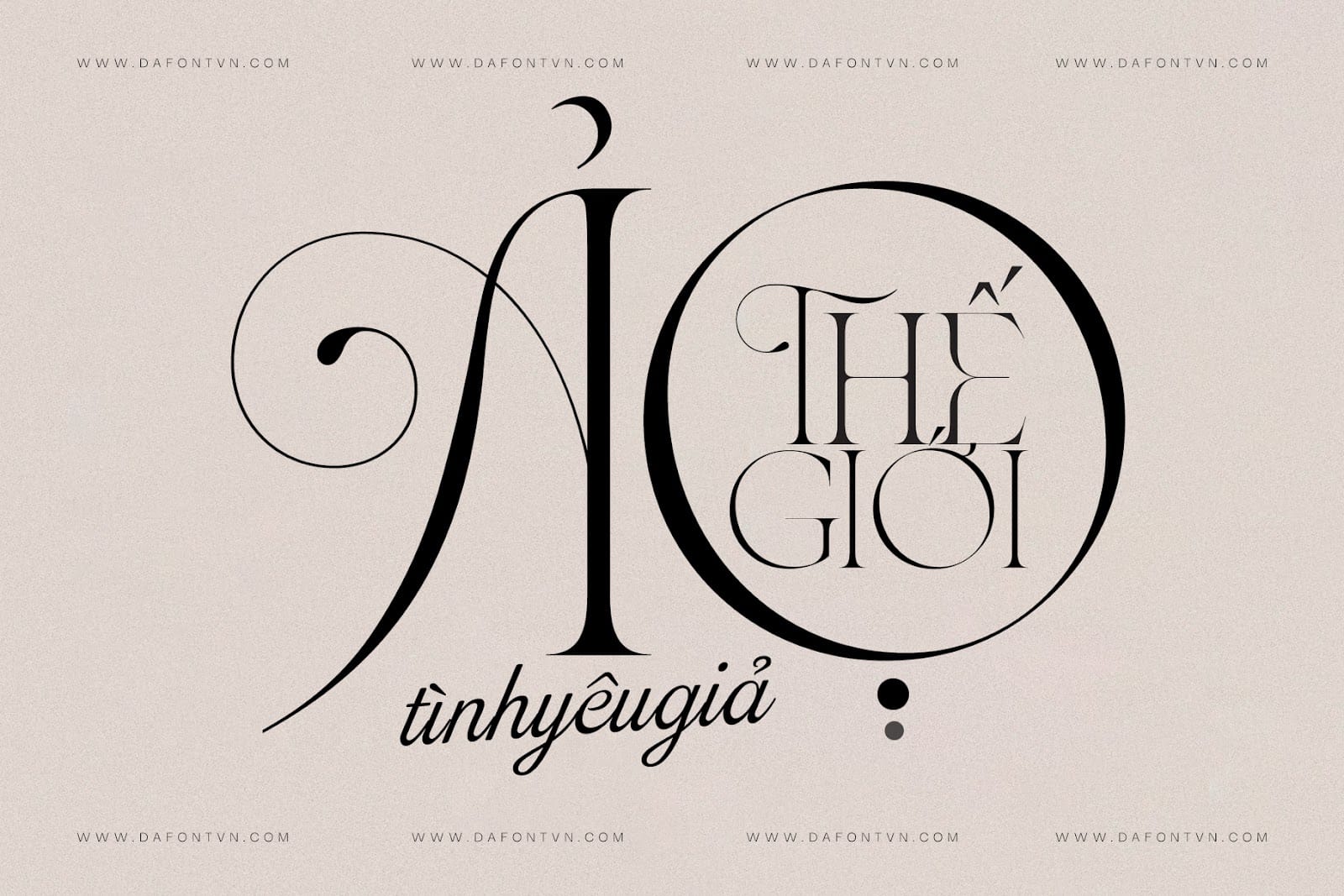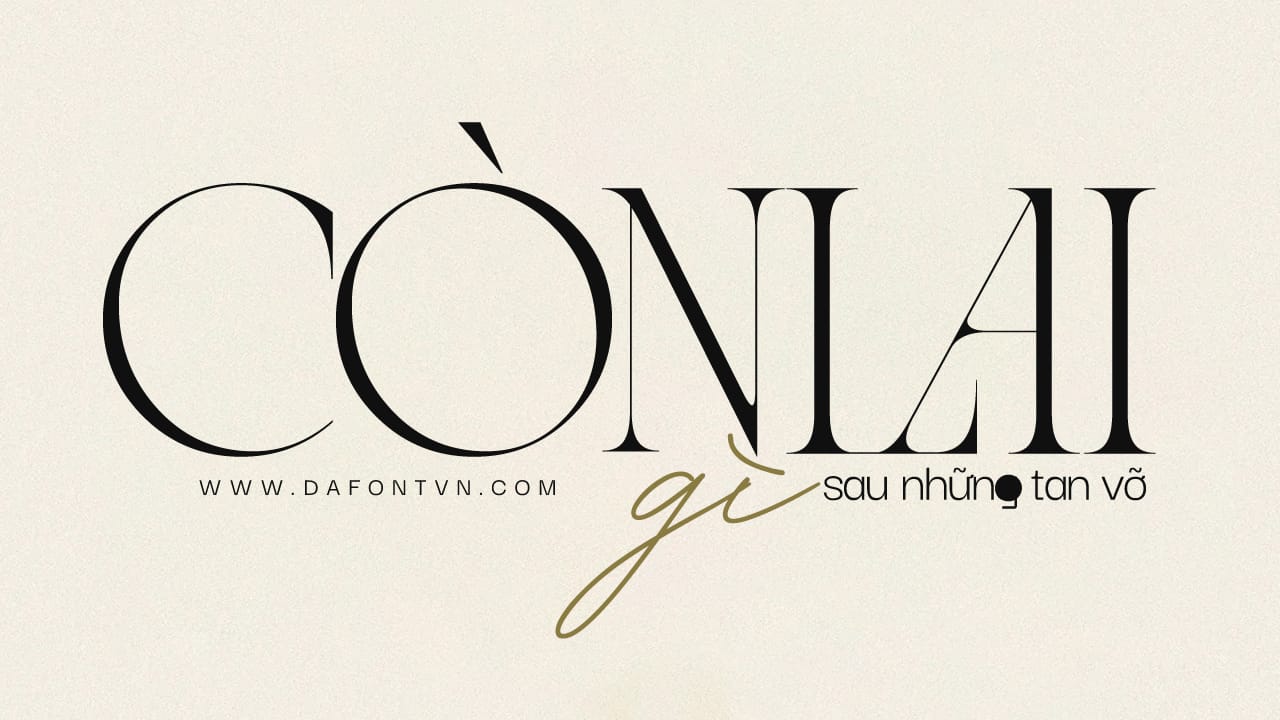
Asther Font là một kiểu chữ hiện đại đẹp mắt lấy cảm hứng từ các tạp chí thời trang, font được thiết kế với những đường nét độc đáo các nét dày-mỏng của nó thể hiện tính hiện đại của nghành thời trang.
Kiểu chữ này bao gồm các chữ hoa đặc biệt và các chữ thường, ngoài ra các nét đặc trưng thay thế và hơn 60 chữ ghép (ligatures) ấn tượng để bạn có thể tạo ra những thiết kế thú vị hơn.
Font Asther là kiểu chữ serif được tạo chủ yếu cho tiêu đề và các văn bản ngắn và rất phù hợp cho quảng cáo, nhãn hiệu, tạp chí, biểu trưng, bao bì, tiêu đề, thiết kế biên tập hoặc bất kỳ thiết kế nào khác mang tính hiện đại và cổ điển.
Font Asther Việt hóa đầy đủ, kerning và chỉnh sửa cũng như tối ưu để sử dụng trên bất kỳ phần mềm hoặc ứng dụng. Để truy cập vào Stylistic Alternates, bạn cần có phần mềm hỗ trợ glyphs như Photoshop và lllustrator.